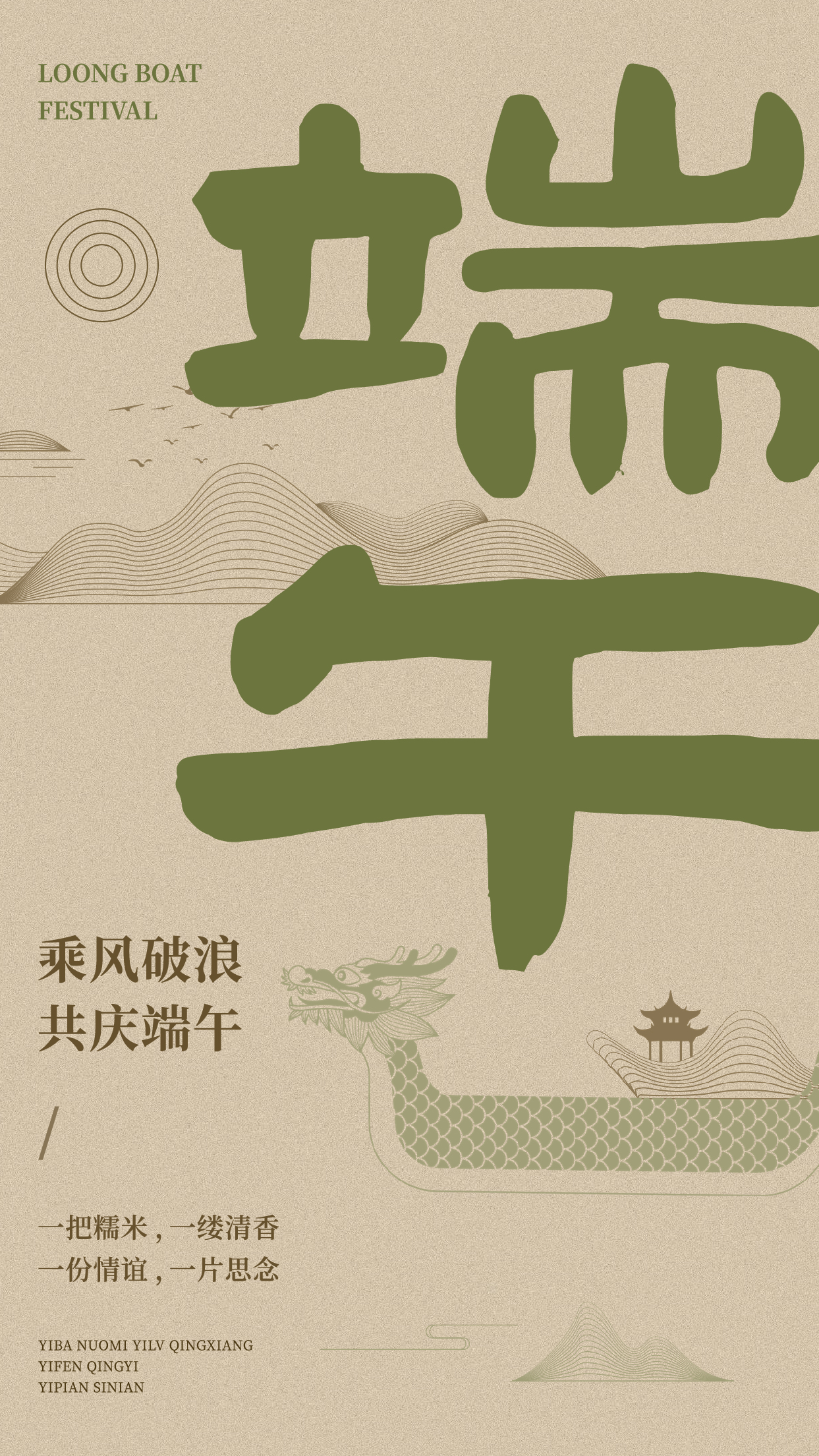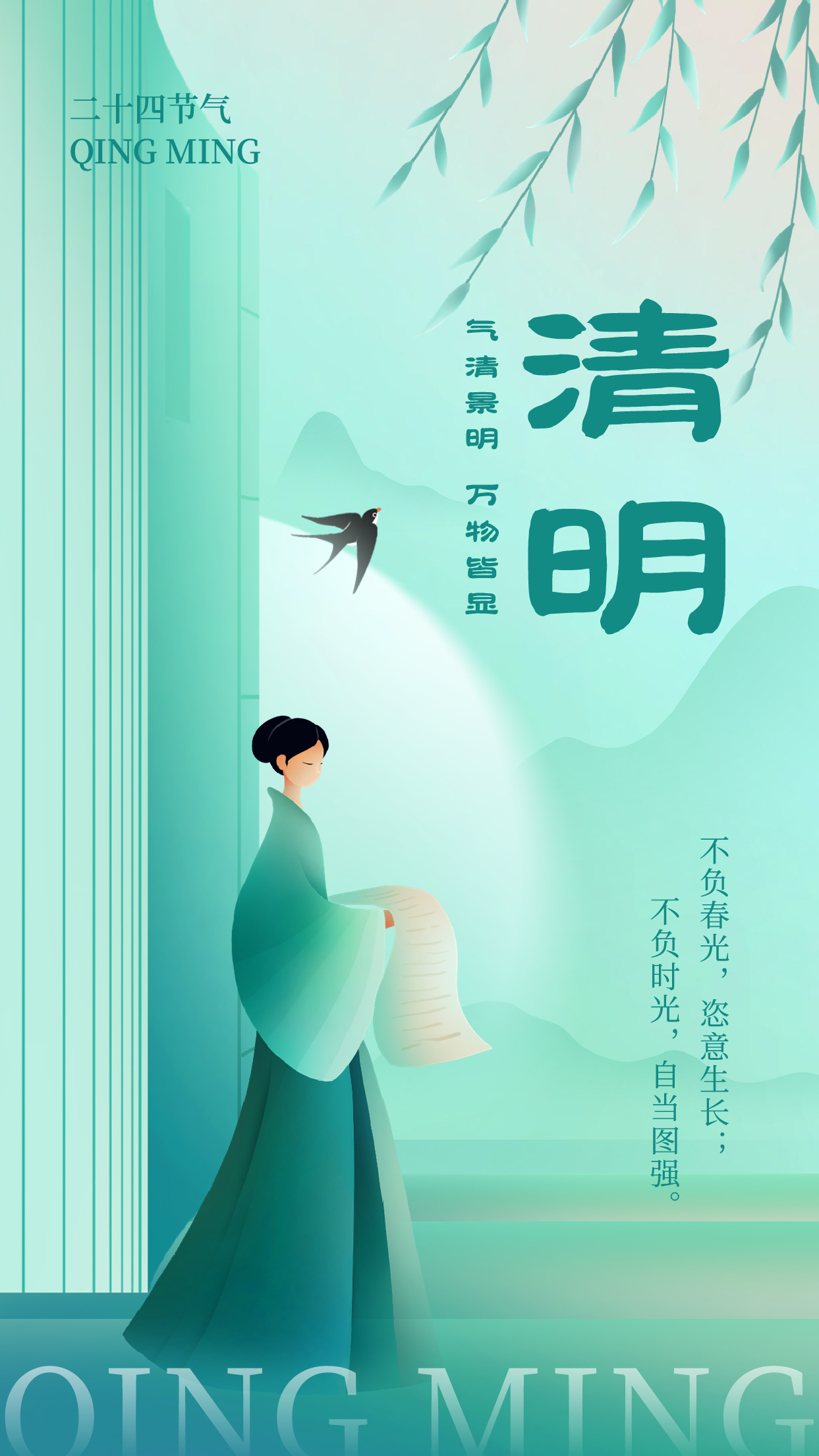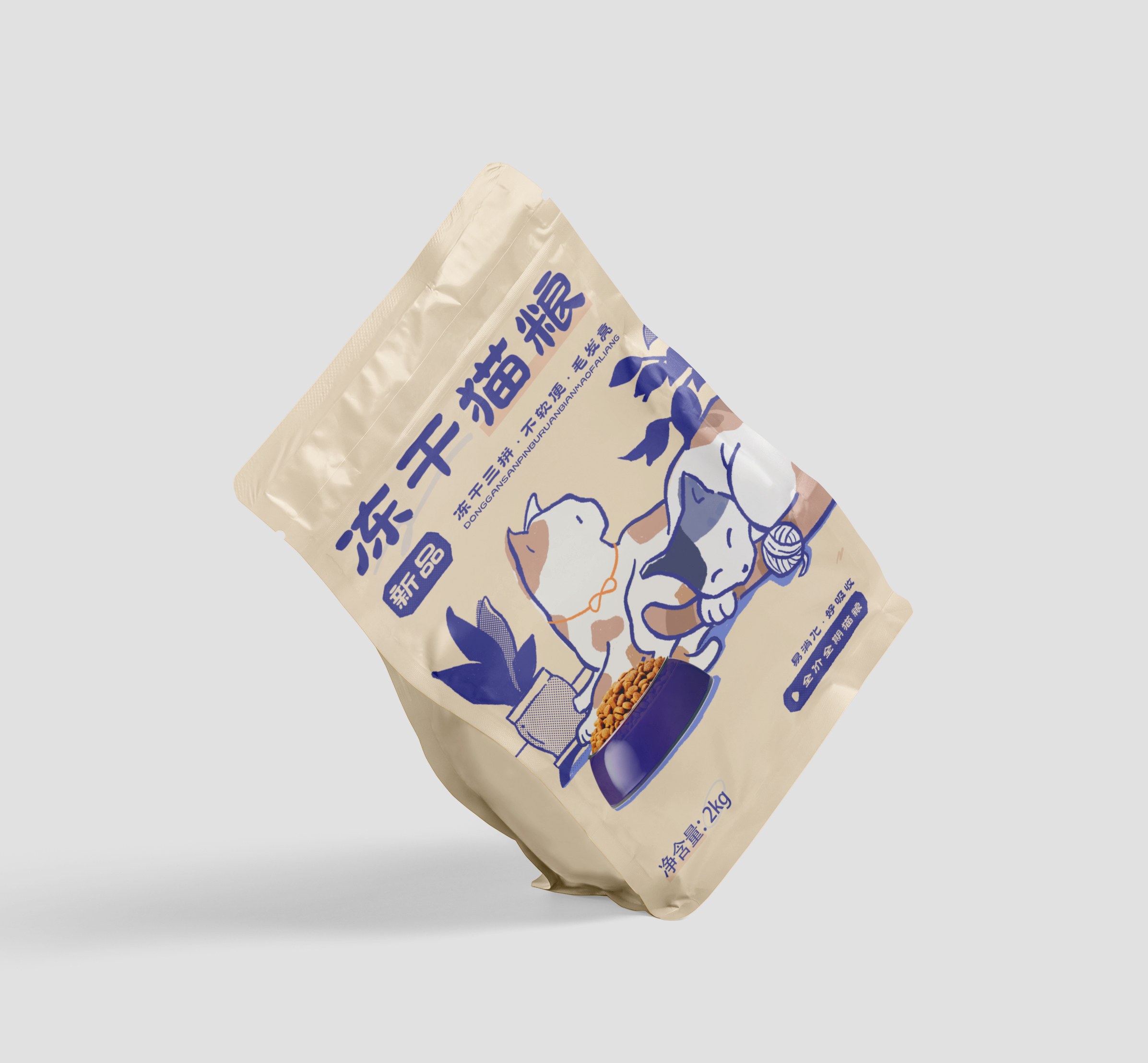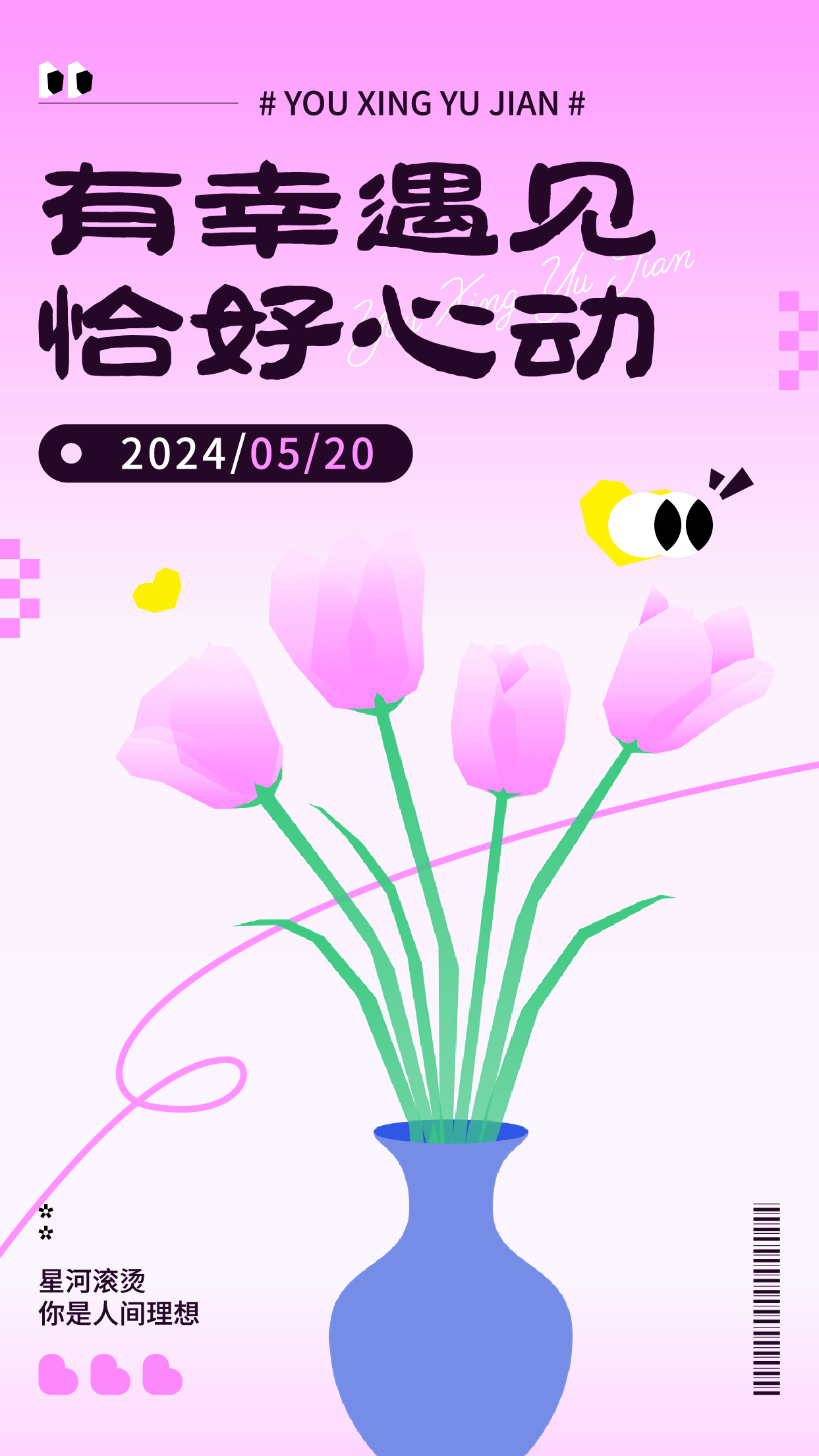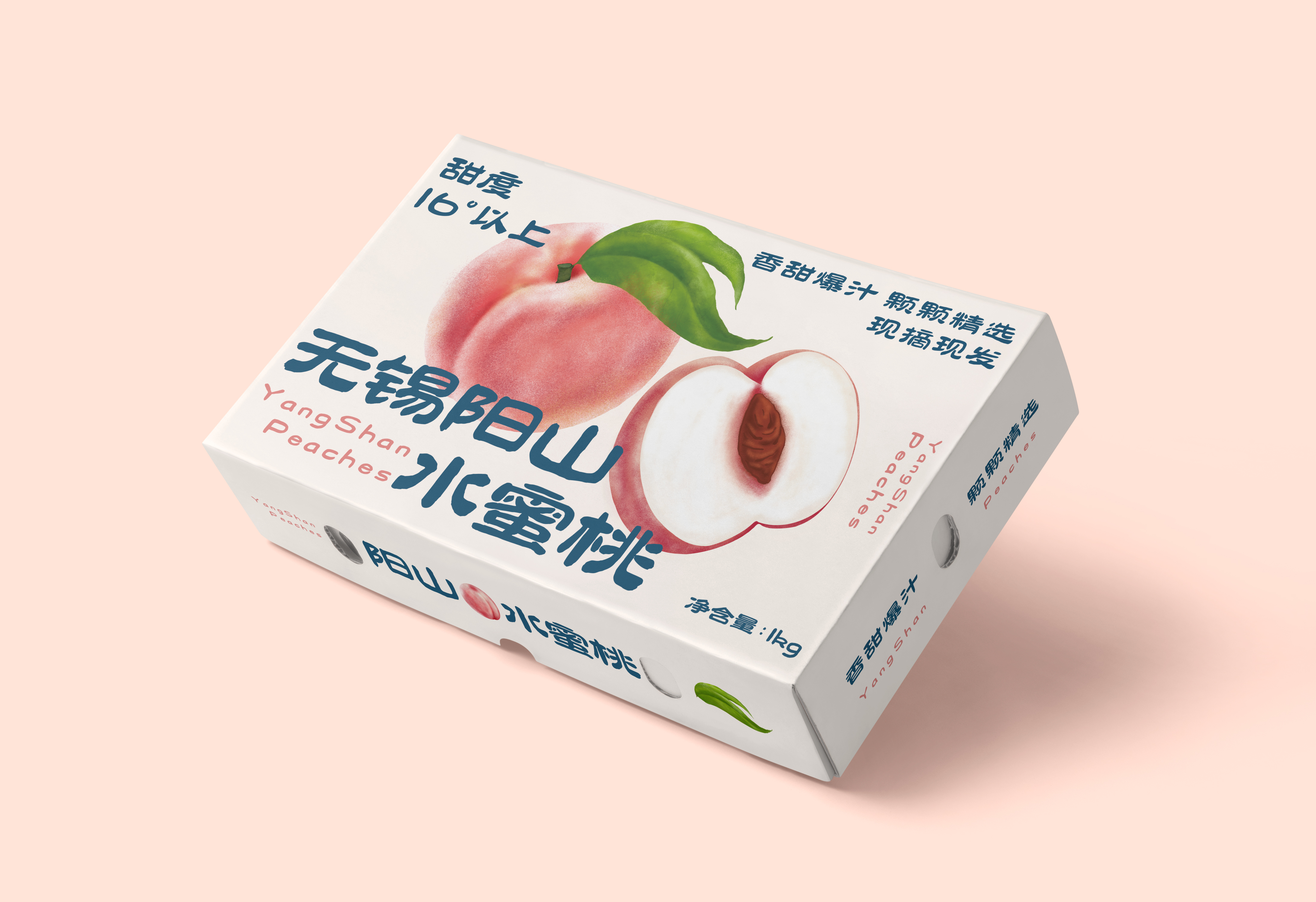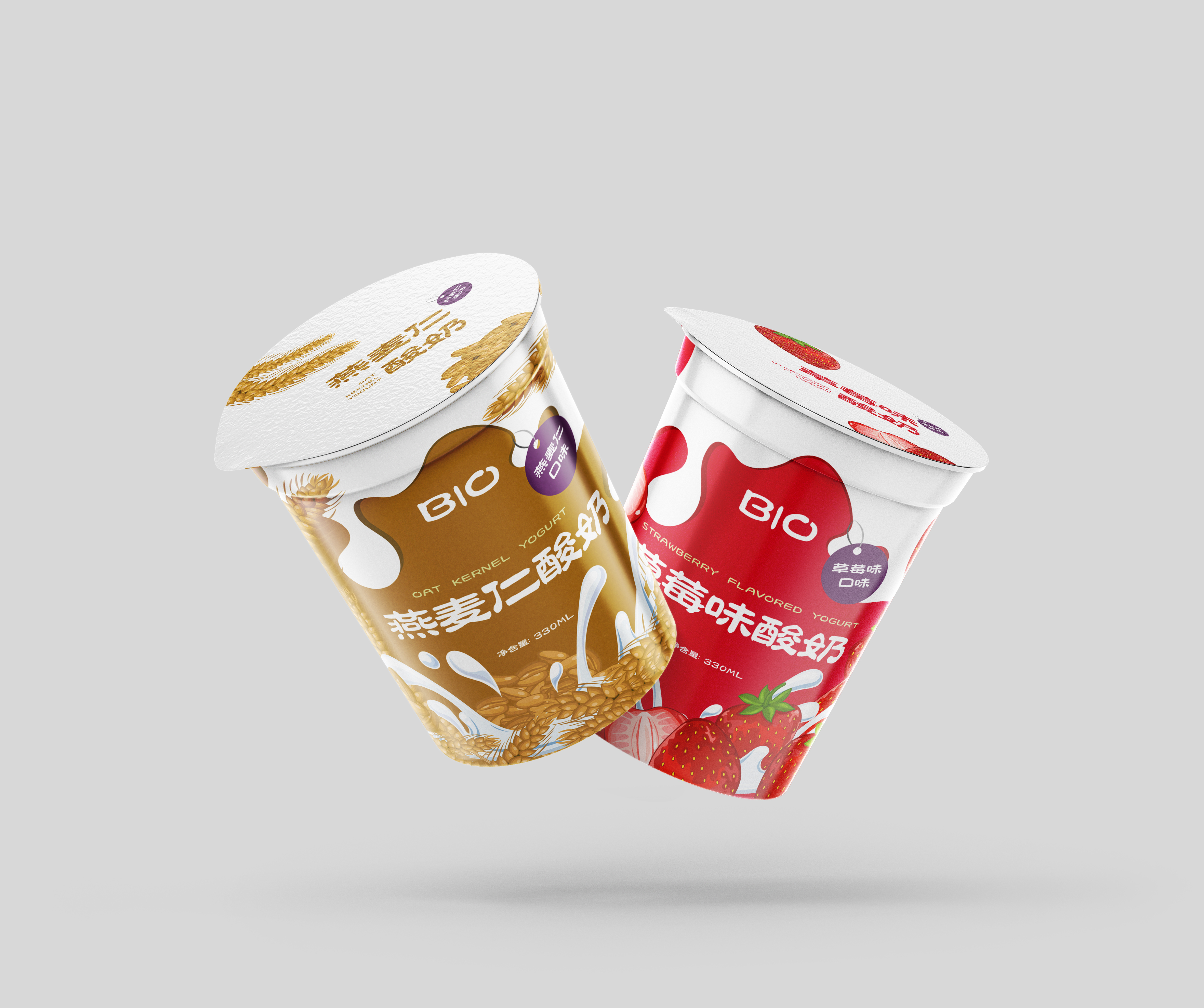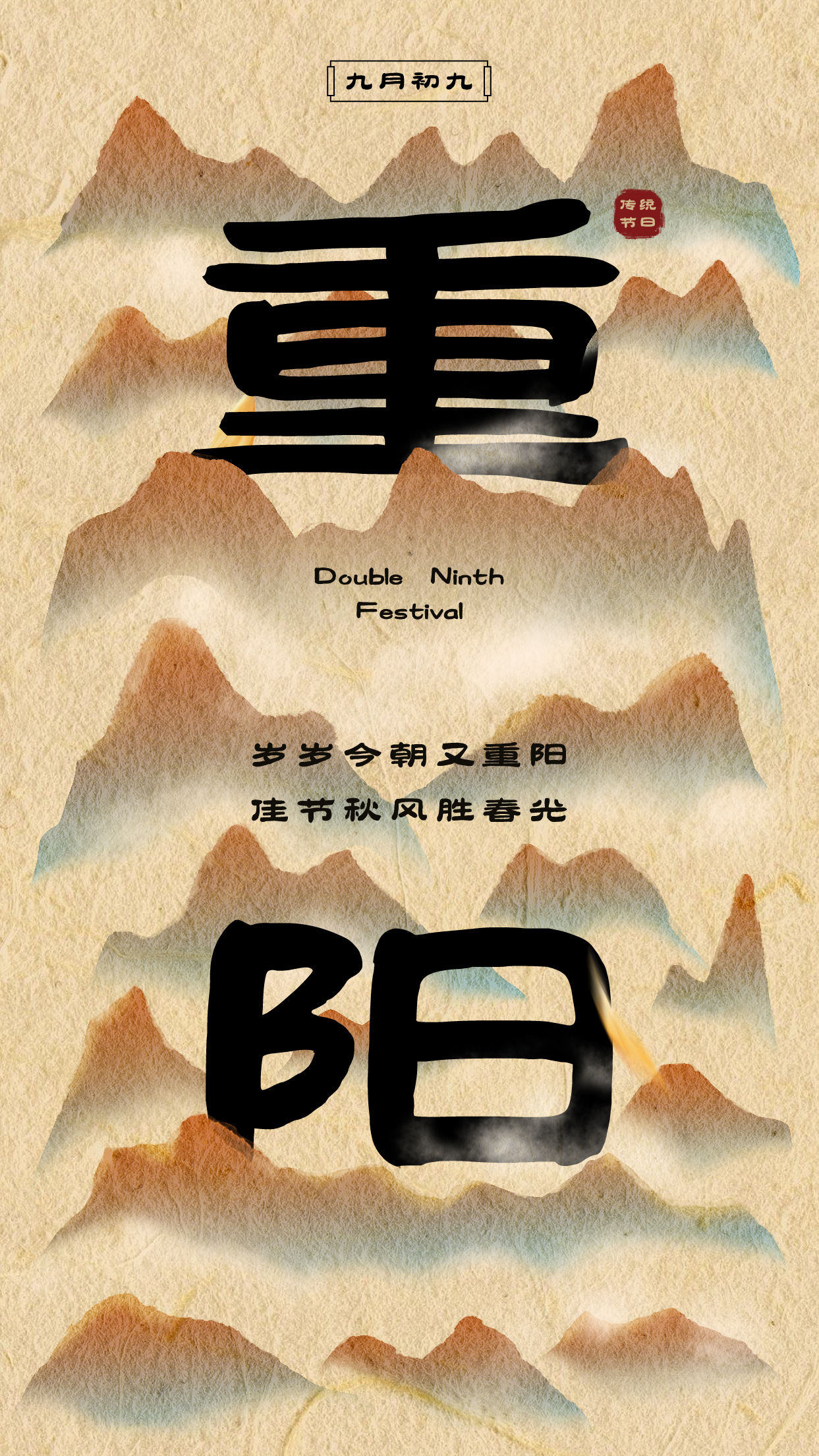
兵克真给隶
兵克真给隶,兵克真给隶,在保留隶书基本特征的基础上,进行了现代化的演绎。继承了隶书特有的波磔与方折笔画,同时融入了现代设计的简洁与流畅,使得字体在视觉上既保留了古朴的韵味,又不失现代感,传达出庄重、古朴、沉稳的美学理念。适用于高端品牌与广告设计、标志设计、书籍设计、海报设计、文化展览与艺术品、平面应用等视觉场景。